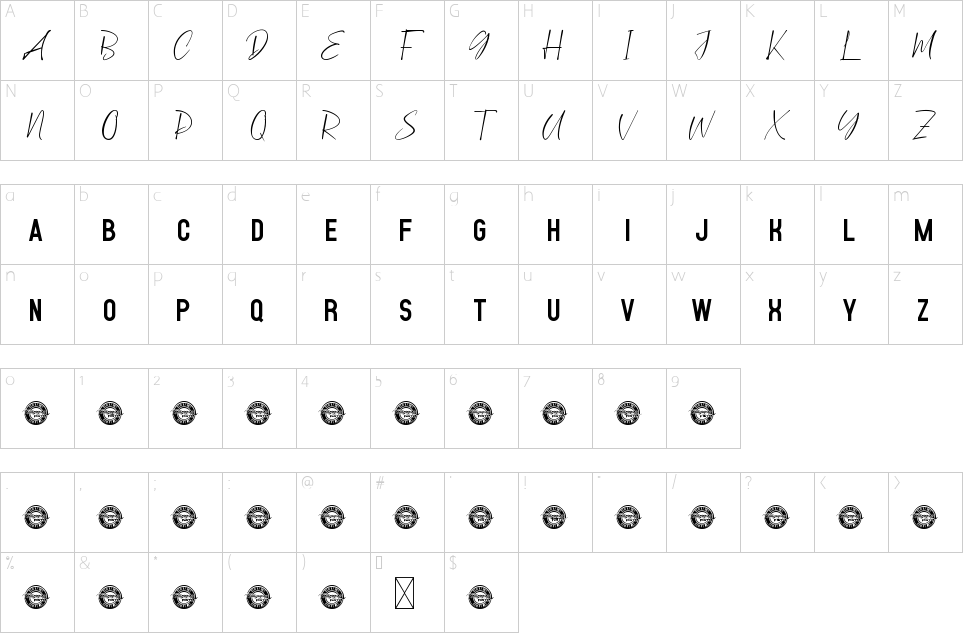
A Dreamy Lanie é uma fonte gráfica ideal para quem busca uma aparição suave e elegante em seus projetos digitais. Desenvolvida pela CalligraphyFont, essa fonte vem com um toque delicado que se destaca nos textos de título e subtítulo, criando um visual agradável e sofisticado. Oferecida para sistemas Windows e Mac, Dreamy Lanie é uma escolha perfeita para designers que desejam adicionar uma nota doce e mágica em seus designs sem comprometer a legibilidade. Com apenas 221 downloads, essa fonte se destaca por sua singularidade e beleza única. Não hesite em explorar as nuances sutis desta tipografia, ideal tanto para aplicativos de design pessoal quanto para trabalhos profissionais que buscam um toque diferenciado.